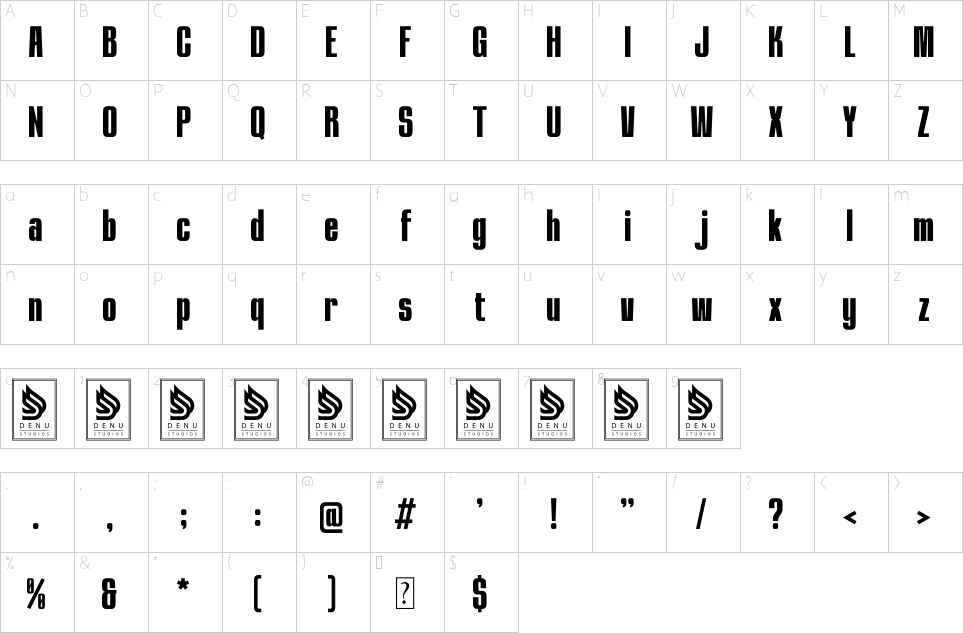
Descubra a elegância de Metroway, uma fonte de linhas suaves e moderna que combina perfeitamente em qualquer projeto de design. Desenvolvida por Denustudios, a Metroway é uma escolha ideal para designers que buscam uma fonte minimalista e versátil. Com seus 1001 Free Fonts, você encontra uma gama de opções gratuitas que se adequam a diversos estilos e necessidades, e a Metroway é certamente uma fonte que merece destaque. Seja para criações de websites, materiais gráficos ou até mesmo para aplicativos, a Metroway oferece um visual atraente e fácil de usar. Com uma aparência simples e limpa, ela combina perfeitamente com qualquer layout e se destaca em diferentes tamanhos e contextos. Fique à espera de mais recursos gratuitos de design aqui no site, sempre buscando a melhor experiência para os nossos usuários.